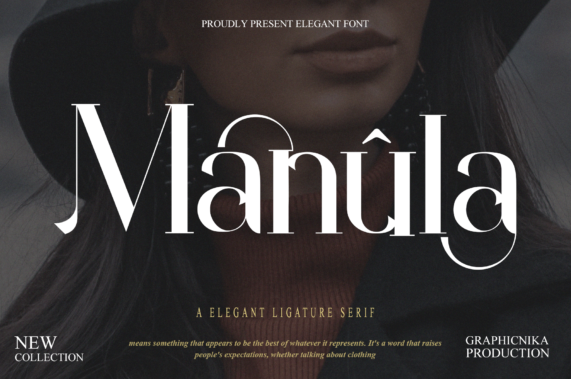
[Creativefabrica] Manula Font (2021)
Manula - это элегантный и выразительный шрифт с засечками.
С его помощью можно воплотить в жизнь самые разные идеи, начиная от открыток, брендинга, этикеток и заканчивая многим другим.
Смело добавляйте его в свои любимые творения и позвольте себе поразиться полученному результату.